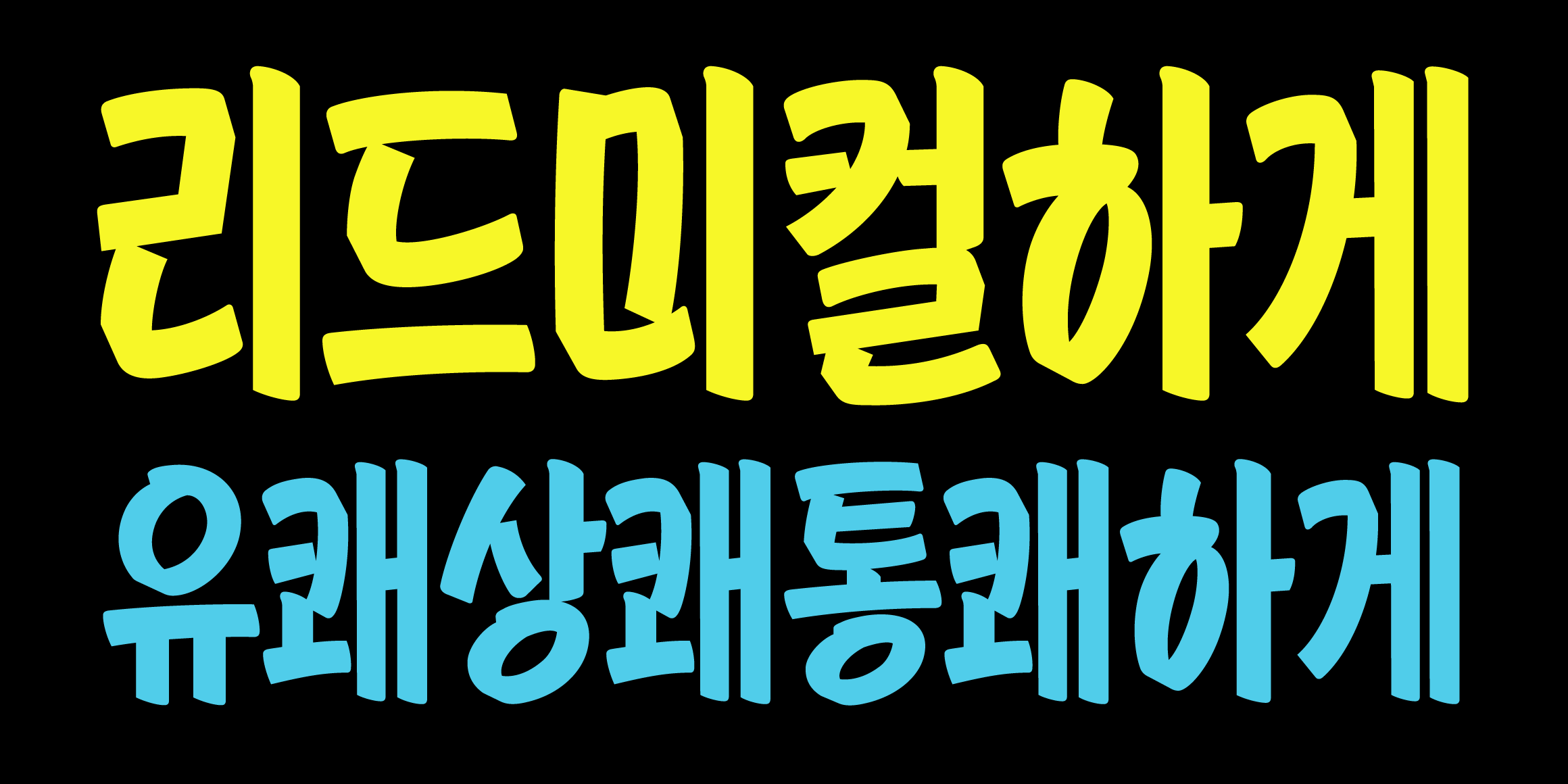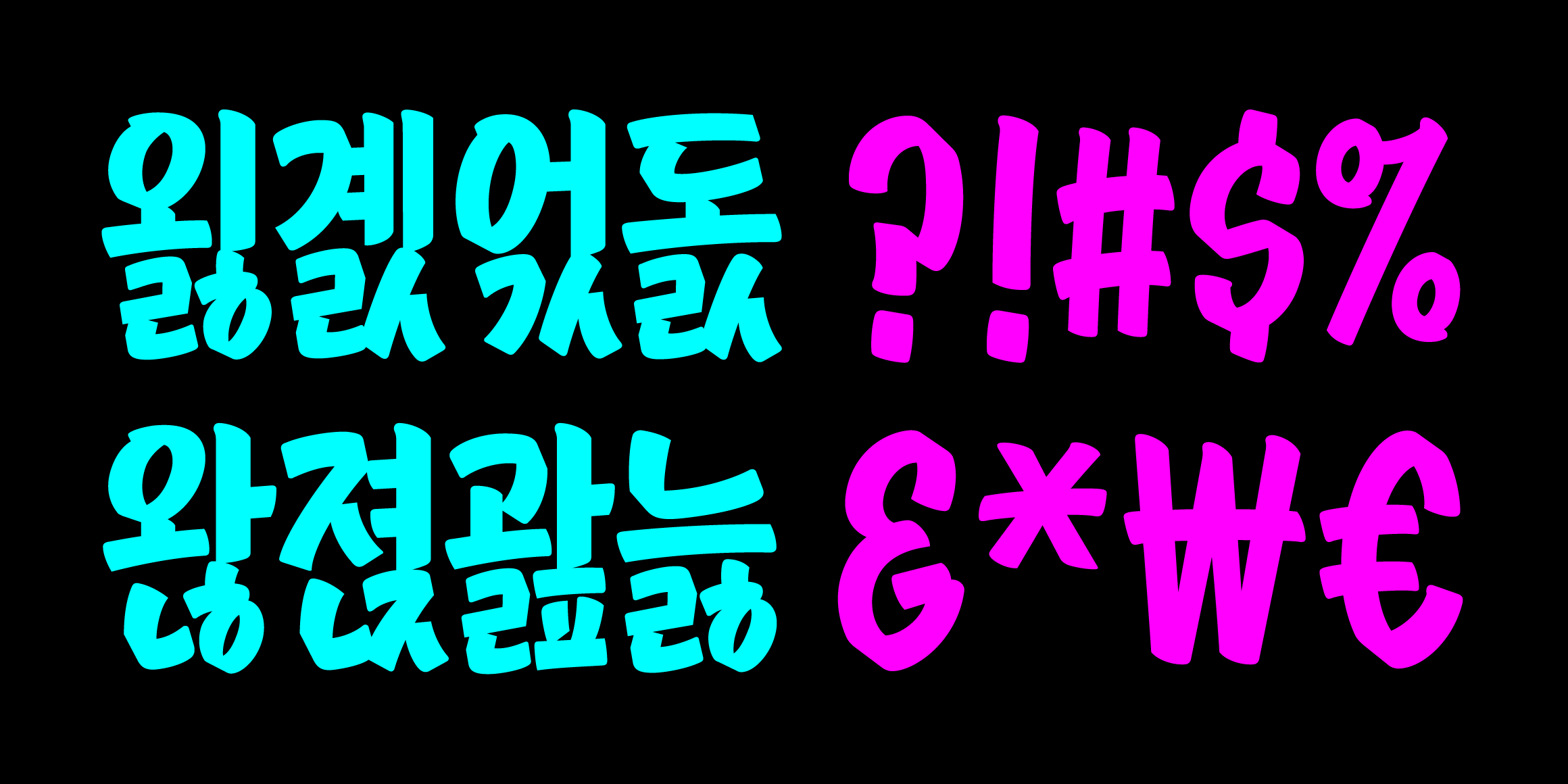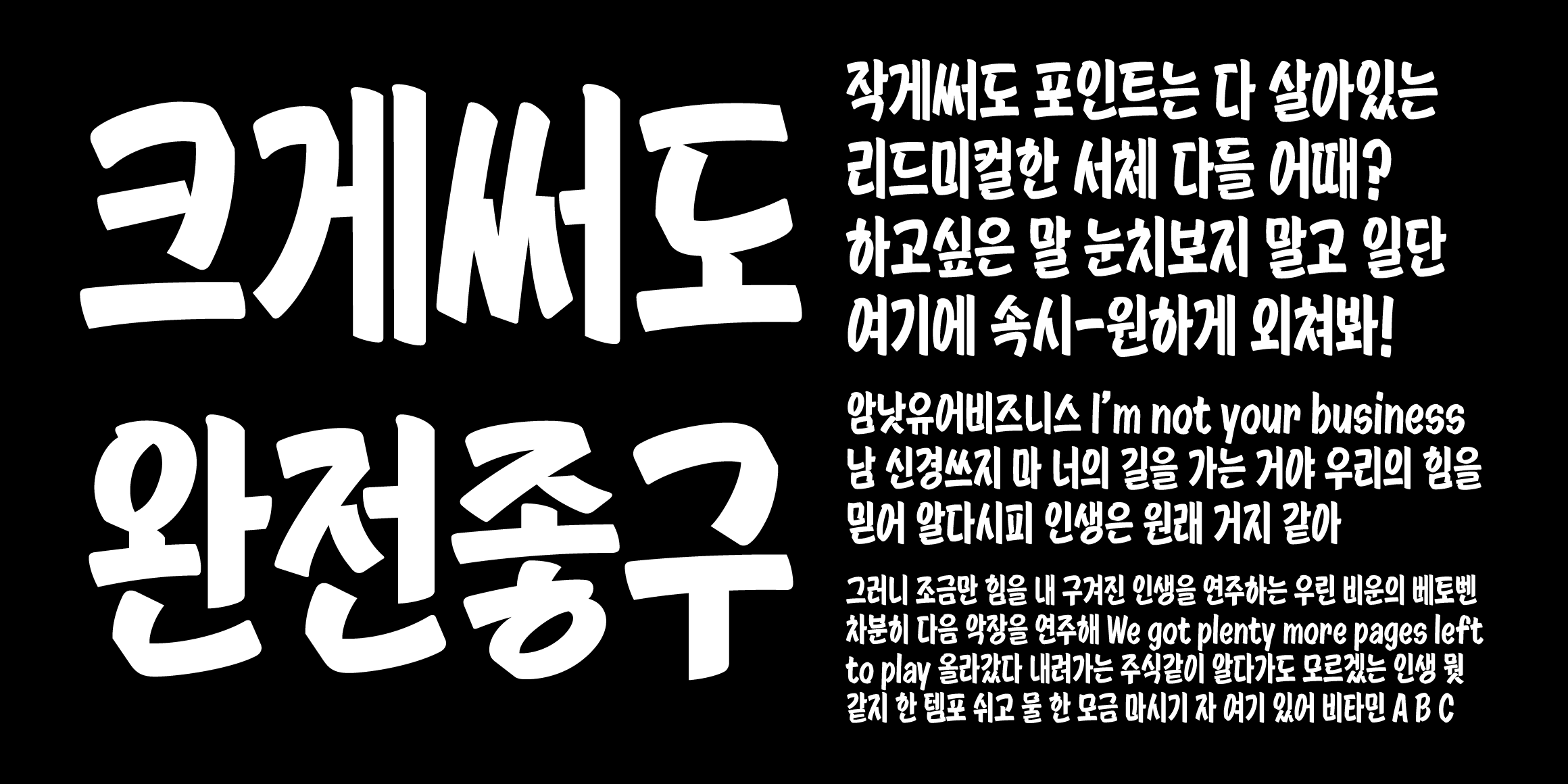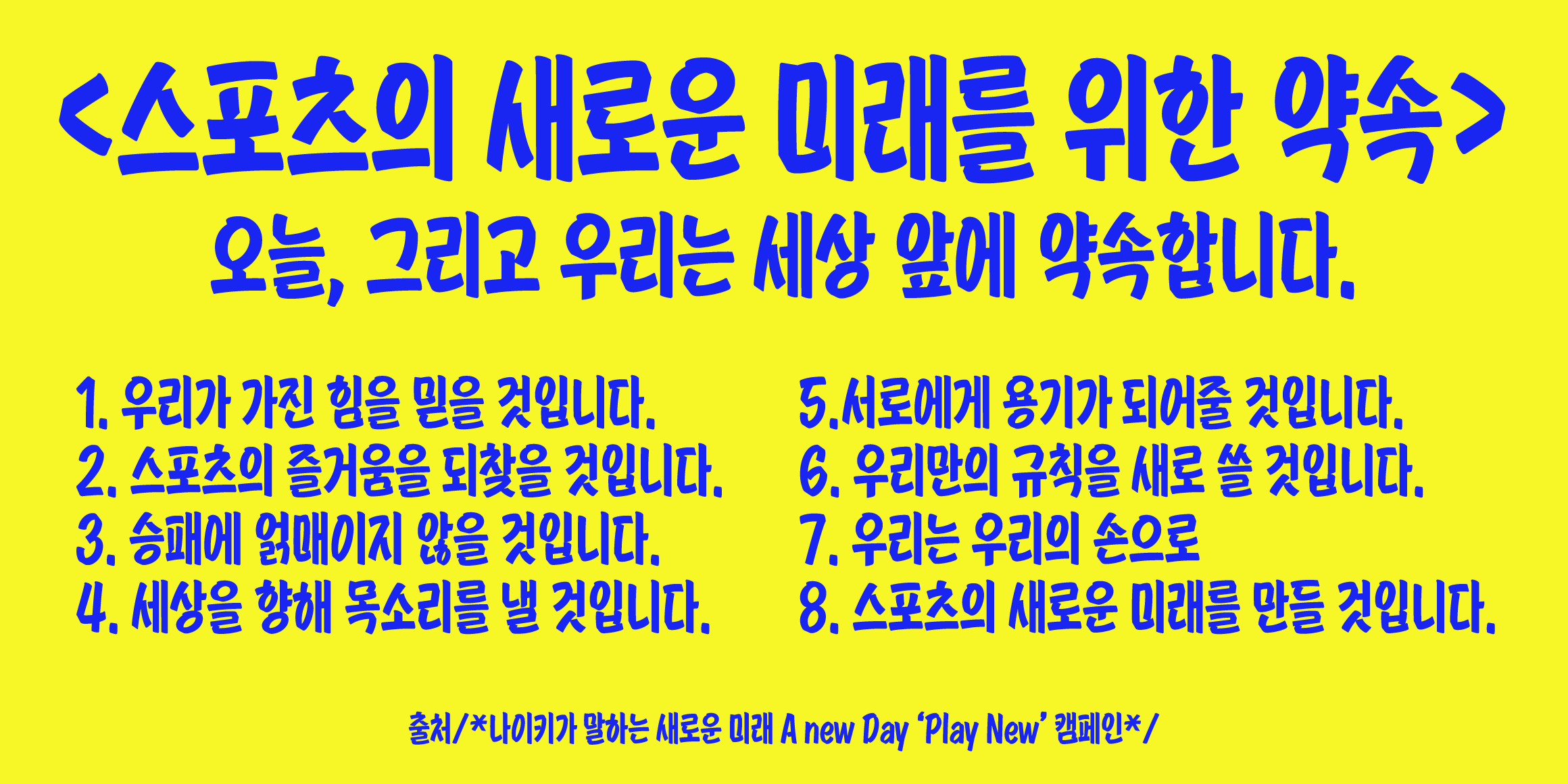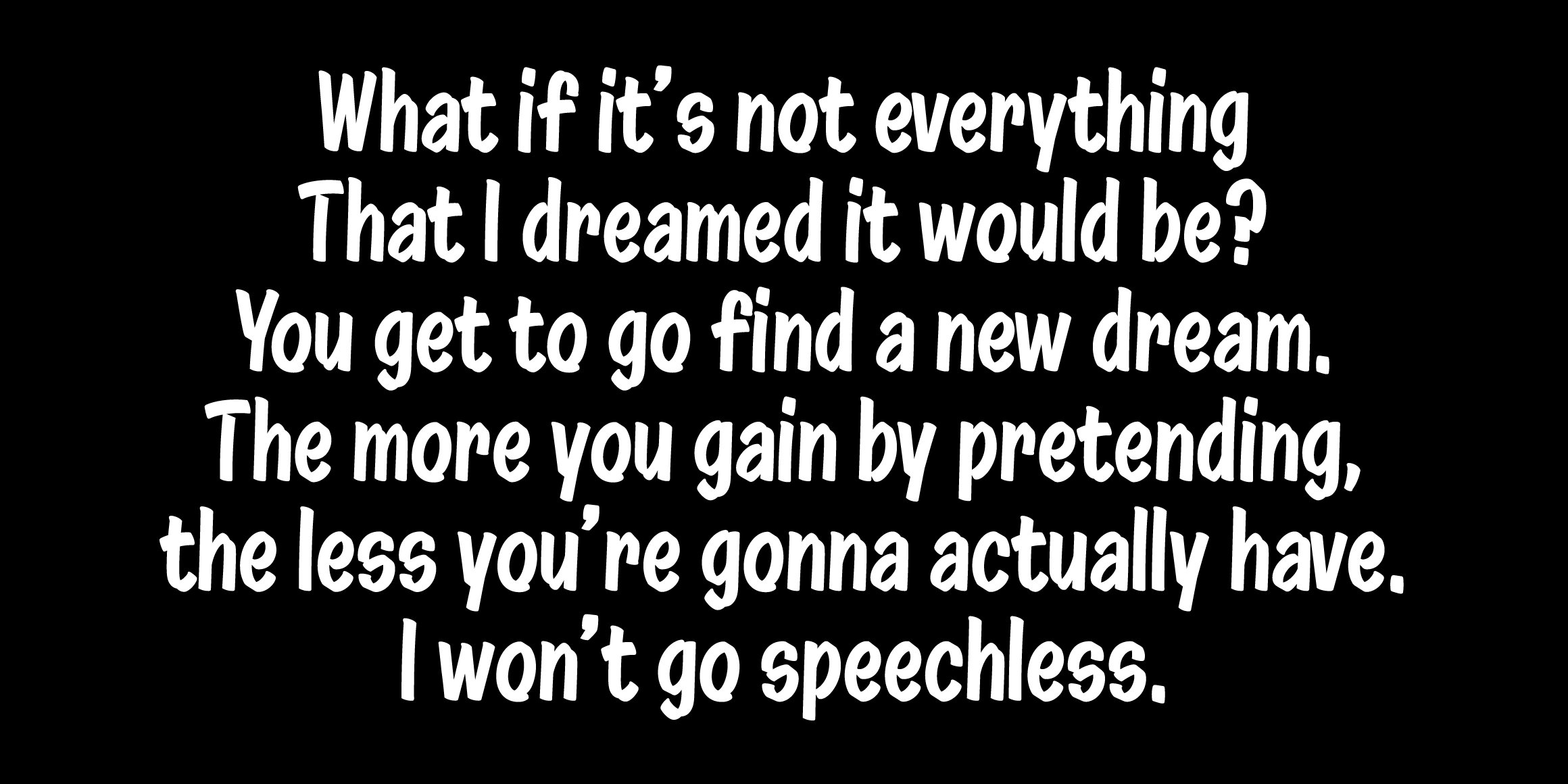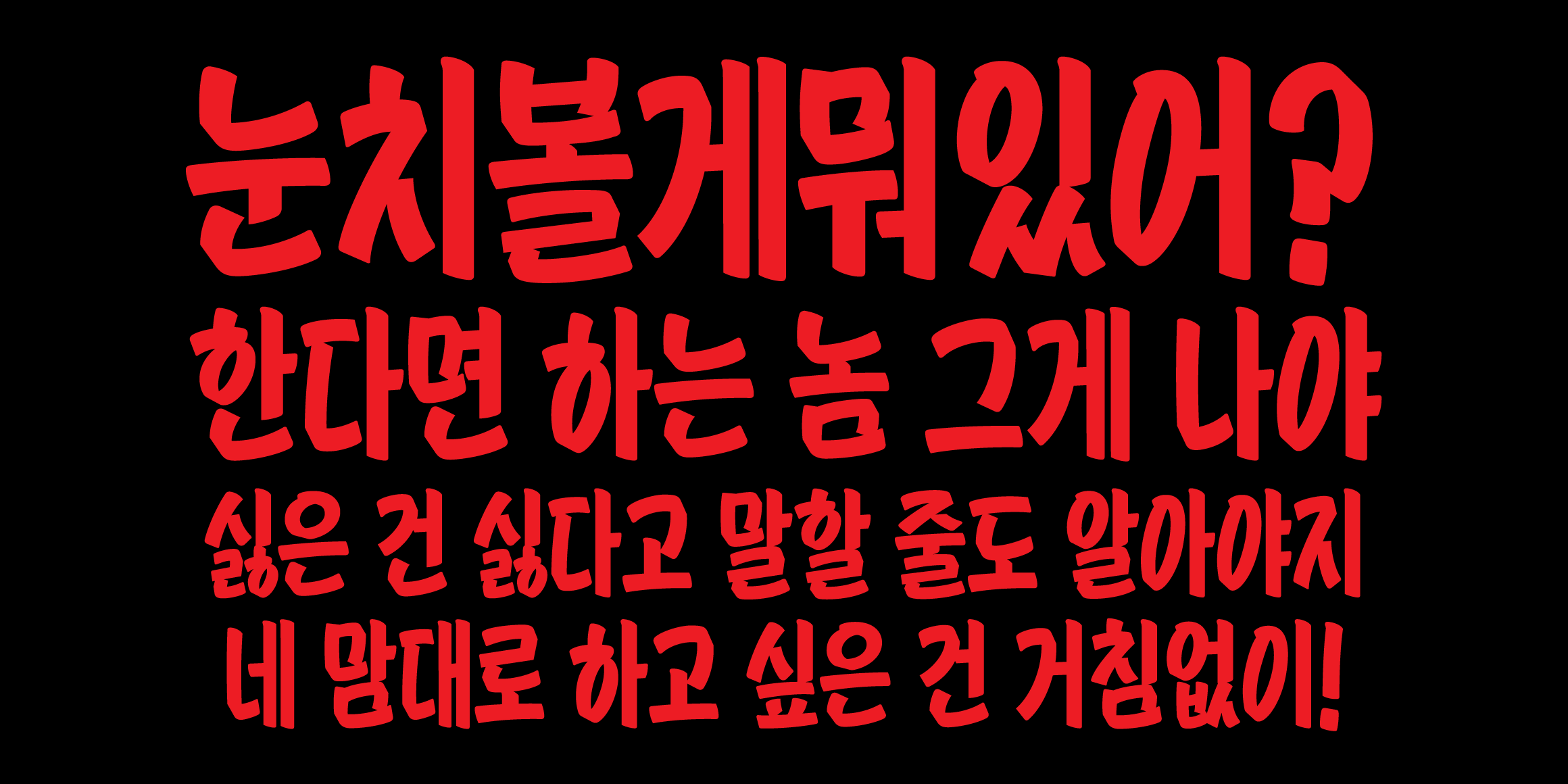
빠른 속도감이 느껴지는 거침없는 획 표현과 유기적인 곡률 형태로 서체의 자유분방함이 특징입니다. 특히 길쭉한 네모 틀에 꽉 찬 구조를 지녀 한정된 공간에서도 많은 양의 메시지를 담을 수 있기에 강한 주목성과 호소력이 필요한 문장에 더욱 어울리는 서체입니다.
굵은 weight를 가지지만 마커 펜에서 나타나는 자소의 독특한 형태(ㅇ, ㅎ)와 질감이 반영되어 서체의 차별성을 주었습니다. 손글씨 기법으로 휴머니티한 인상이 강하기 때문에 낯설지 않은 친근한 인상을 줄 수 있습니다.